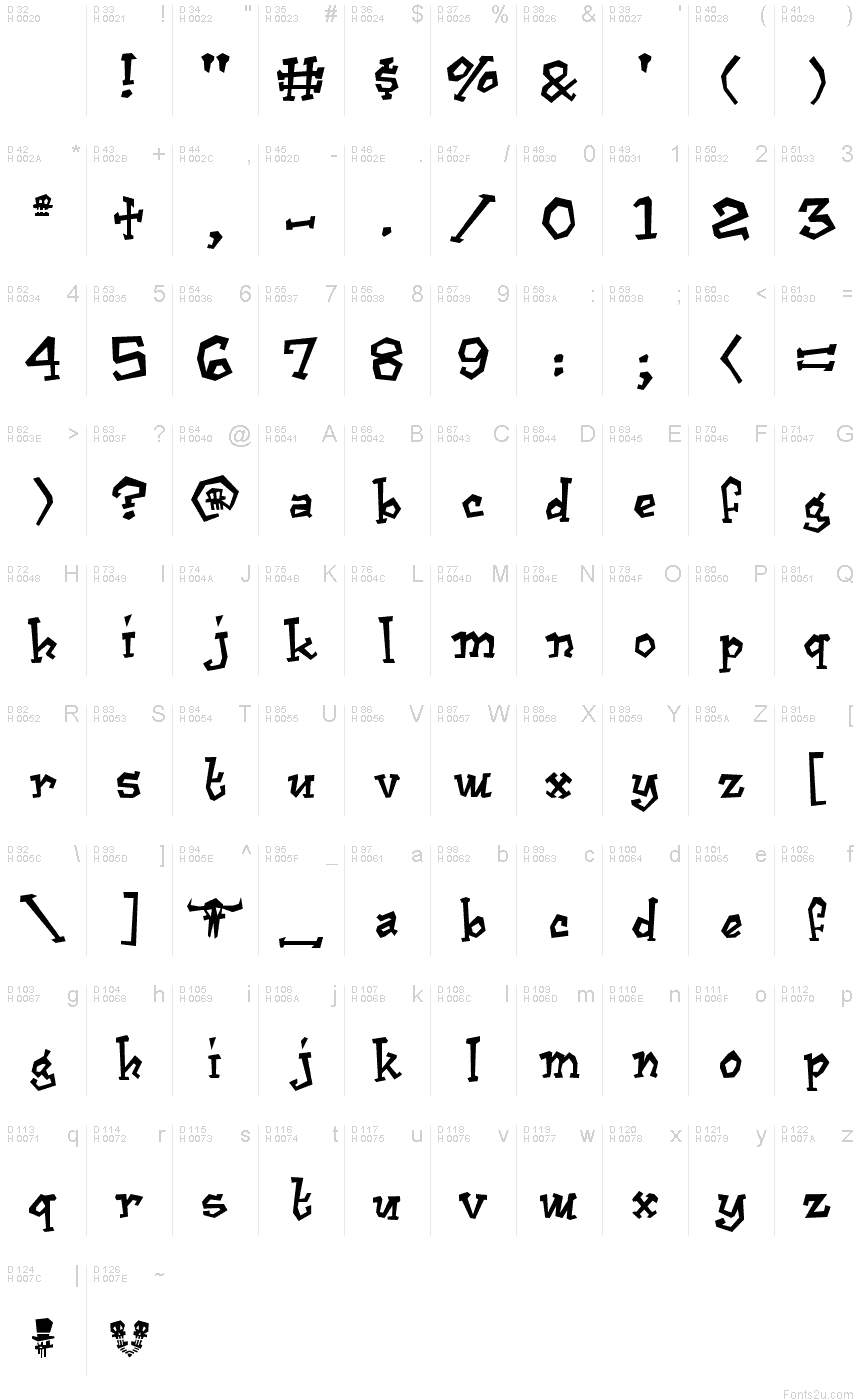
Cajun Boogie od Nate’a Piekosa to darmowy, nieco zniekształcony krój displayowy, który wygląda, jakby został naszkicowany na serwetce w barze podczas nocnej imprezy. Jego poszarpane kreski, krzywe kąty i delikatnie „cieknący” charakter nadają każdemu słowu luźny, dziki rytm – nic nie stoi tu prosto, a jednak wszystko tworzy spójną całość. Litery sprawiają wrażenie rysowanych tuszem i wycinanych ręcznie, przypominając surowe plakaty przyklejone do słupa przed zadymionym klubem.
Dzięki Cajun Boogie Twoje nagłówki natychmiast nabierają dzikiej, mistycznej energii, która świetnie sprawdza się w grafikach na Halloween, plakatach koncertowych, tytułach horrorów komediowych, etykietach ostrych sosów, logotypach gier czy wyrazistych miniaturkach na YouTube. Ten darmowy font najlepiej prezentuje się w dużych rozmiarach, gdzie jego surowe krawędzie mogą w pełni pokazać swój charakter. Aby zachować czytelność, połącz Cajun Boogie z prostym, czystym krojem bezszeryfowym w tekście głównym, pozwalając nagłówkowi na odrobinę szaleństwa.